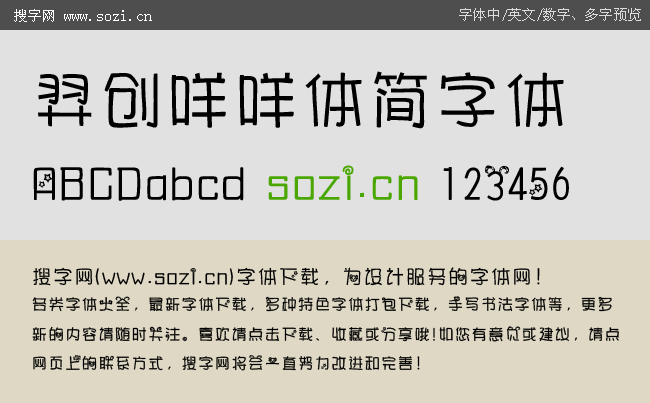
羿創(chuàng)咩咩體簡(jiǎn)字體
搜字網(wǎng)給大家提供一款羿創(chuàng)咩咩體簡(jiǎn)字體手機(jī)中文字體下載。這款手機(jī)字體是以一款POP風(fēng)格的卡通字體為原形,字體間嵌入了可愛(ài)的卡通圖案,是非常可愛(ài)的一款字體,特別適合喜歡手機(jī)字體個(gè)性一些的朋友在手機(jī)上安裝使用。